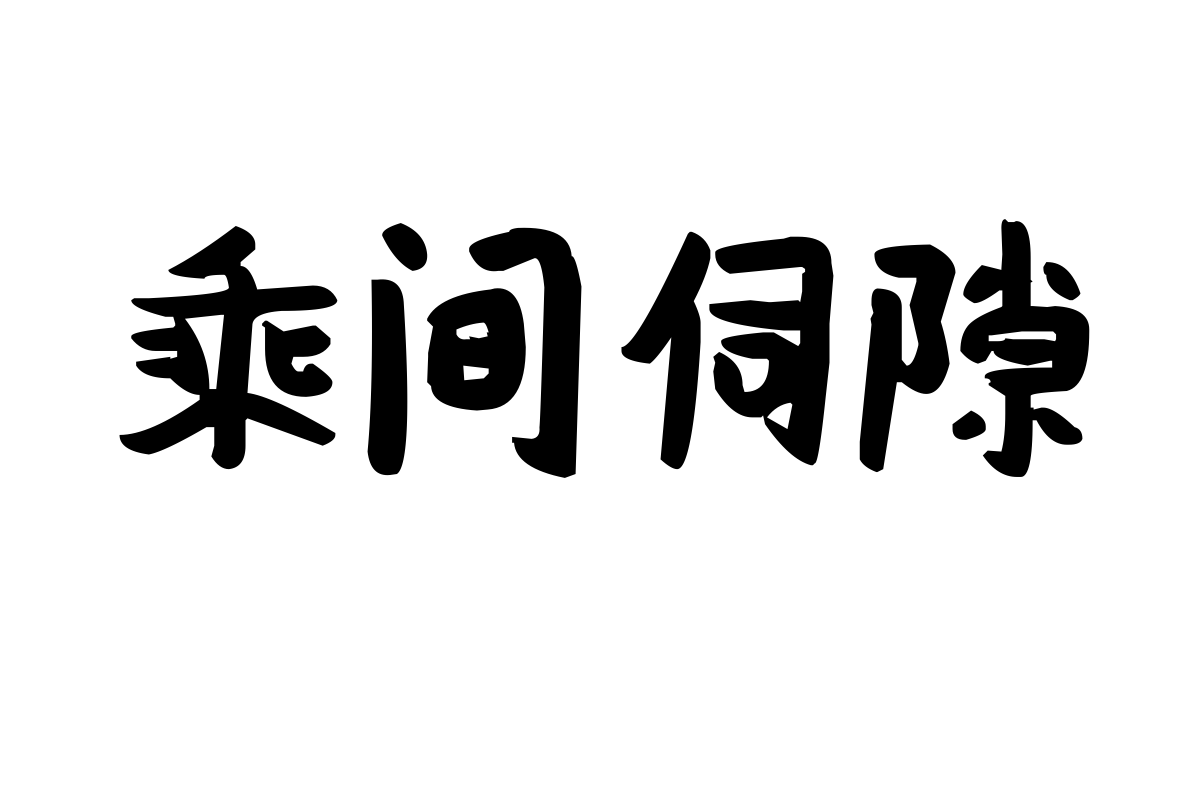
汉标毛遂体是一种具有独特风格和特色的中文字体。它源自中国,具有浓厚的传统文化气息,同时融入了现代设计元素,使得字体既保留了古典韵味,又不失现代感。
汉标毛遂体的特点如下:
1. 字形结构:汉标毛遂体的字形结构紧凑而富有变化,笔画流畅自然,线条粗细有度,给人一种优雅、大方的感觉。同时,字体的字形具有一定的规律性,易于识别和记忆。
2. 风格特点:汉标毛遂体具有独特的风格特点,如笔势圆润、力度适中、节奏感强等。这种风格使得字体具有很强的视觉冲击力,能够吸引读者的注意力,让人过目难忘。
3. 适用范围:汉标毛遂体适用于各种场合,如广告、宣传、设计、出版等。无论是在正式场合还是在日常生活中,汉标毛遂体都能展现出其独特的魅力,为作品增色添彩。
4. 可读性:汉标毛遂体具有良好的可读性,字体大小适中,间距均匀,便于阅读和书写。同时,字体的笔画粗细适中,不会因为过大或过小而影响阅读效果。
总之,汉标毛遂体是一种具有独特风格和特色的中文字体,适合用于各类设计作品中,能够为作品增添一份独特的韵味。